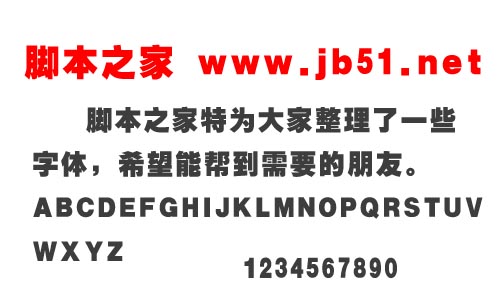
倉頡超粗黑簡(jiǎn)體是一款超粗的黑體字體,風(fēng)格比一般的字體更有特色,連貫字跡顯得干練而不凌亂,清新簡(jiǎn)明,具有很好的視覺感,適合應(yīng)用于藝術(shù)設(shè)計(jì)、平面宣傳設(shè)計(jì)、網(wǎng)頁設(shè)計(jì),書法字帖等領(lǐng)域,歡迎喜歡倉頡超粗黑簡(jiǎn)體字體的朋友前來下載使用。